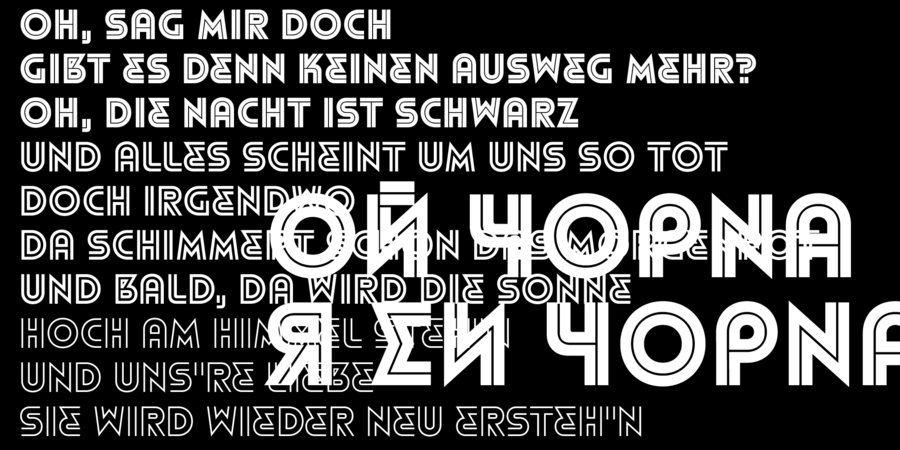
DR Refunk – це смугастий геометричний шрифт у традиціях модернізму. Варіативна гарнітура з латинкою, кирилицею та гречкою. Шрифт розробив Дмитро Растворцев у 2023 році.
Асоціації з сімейством шрифтів DR RefunkОсобистість і характер гарнітури:
сильний, важкий, гучний, модний, оригінальний, виразний, якісний, дзвінкий, позитивний, артистичний, сучасний, міський, музичний, популярний, точний, свіжий, твердий, чіткий, яскравий, помітний, мотивуючий, архітектурний, хіпстерський, святковий, радісний, рівний, неоновий, клубний, молодіжний, сексуальний, манірний, дотепний, грайливий, глянцевий, тусовочний, ритмічний, привабливий, танцювальний, нічний, пульсуючий, мерехтливий, гострий, колючий, електронний, різкий, чистий, легкий, тонкий, ефектний, невагомий, прозорий, повітряний, скляний, дротяний
бар, кафе, інтер'єр, театр, одяг, мода, музика, дизайн, Місто, архітектура, архітектор, розваги, аксесуари, атракціон, прикраса, свято, коктейль, казино, гра, кіно, дискотека, клуб, нічний клуб, телебачення, шоу, вечірка, тусовка, кінотеатр, танці, спорт, танець, рок-н-рол, аквадискотека, туризм, алкоголь, електроніка, гаджет, девайс Гарнітура має ознаки стилів: